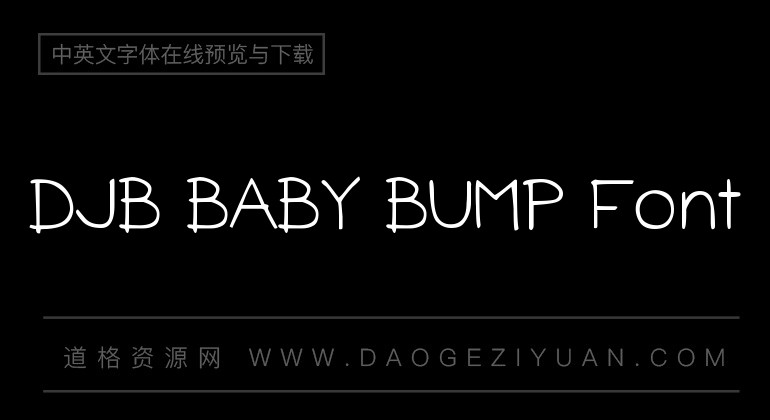
DJB BABY BUMP Font是一种手写风格的字体,设计者为Darcy Baldwin。它的特点是带有一些类似涂鸦的元素,使用起来有一种可爱、活泼的感觉。这种字体适合用于婴儿出生、儿童派对等场合,也可以用于各种手工制品、艺术项目和DIY设计。DJB BABY BUMP Font可以在许多字体网站上免费下载和使用。内容介绍
DJB BABY BUMP Font是一款非常不错的手写艺术字体,具有很好的视觉感,适合于文化类的宣传设计、商业类品牌的广告和产品包装设计以及个性化文字排版等较多场景。